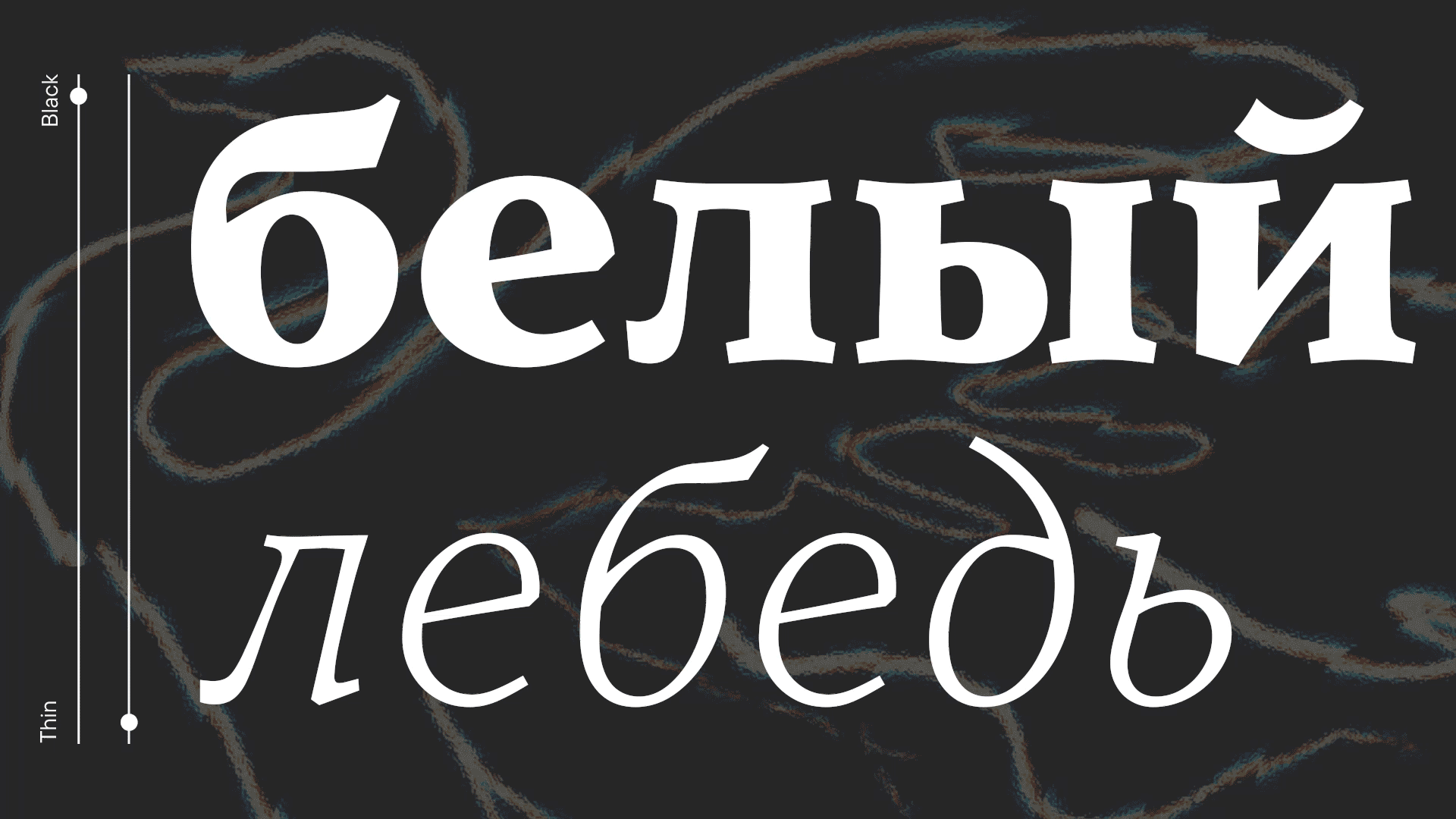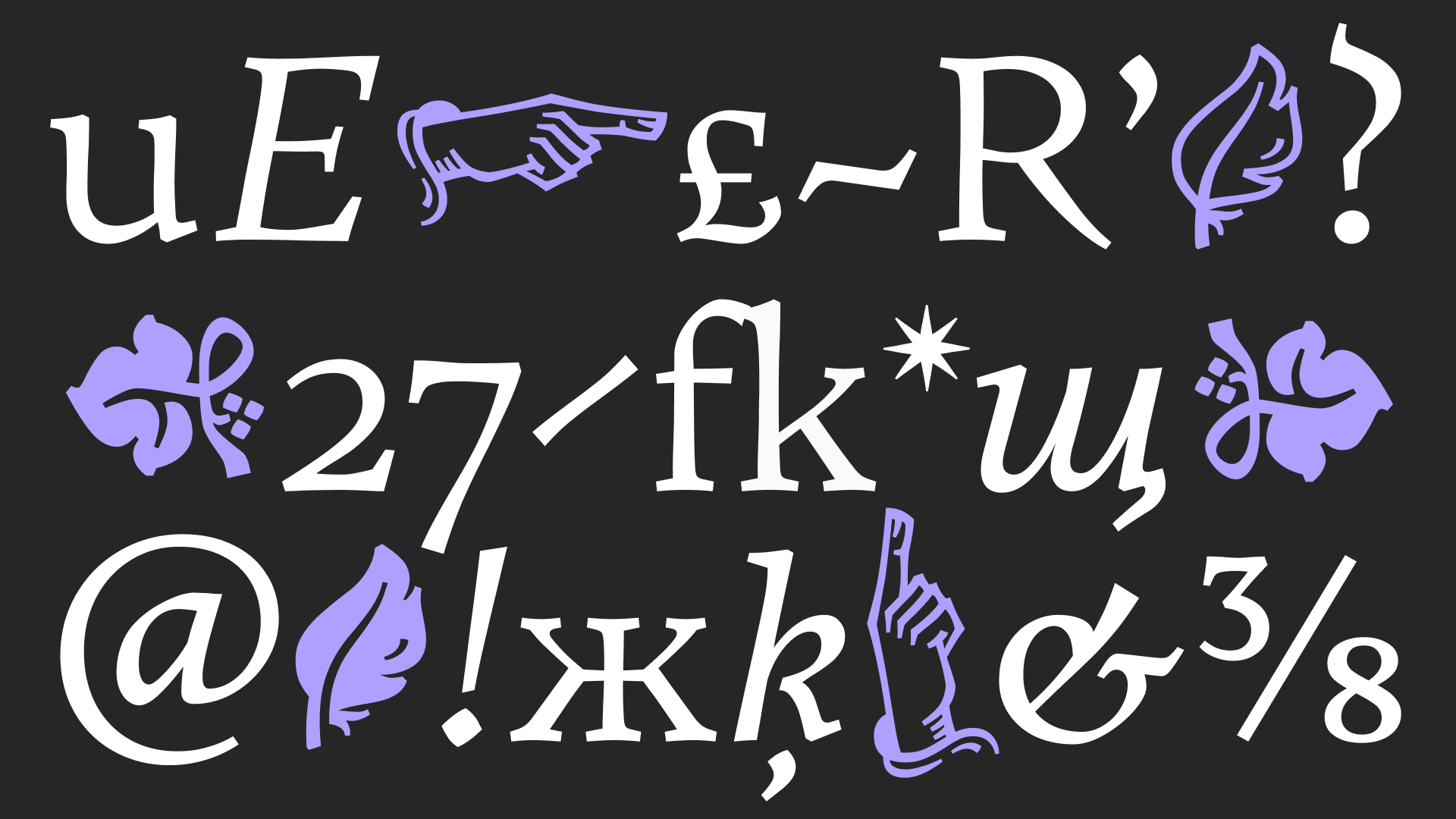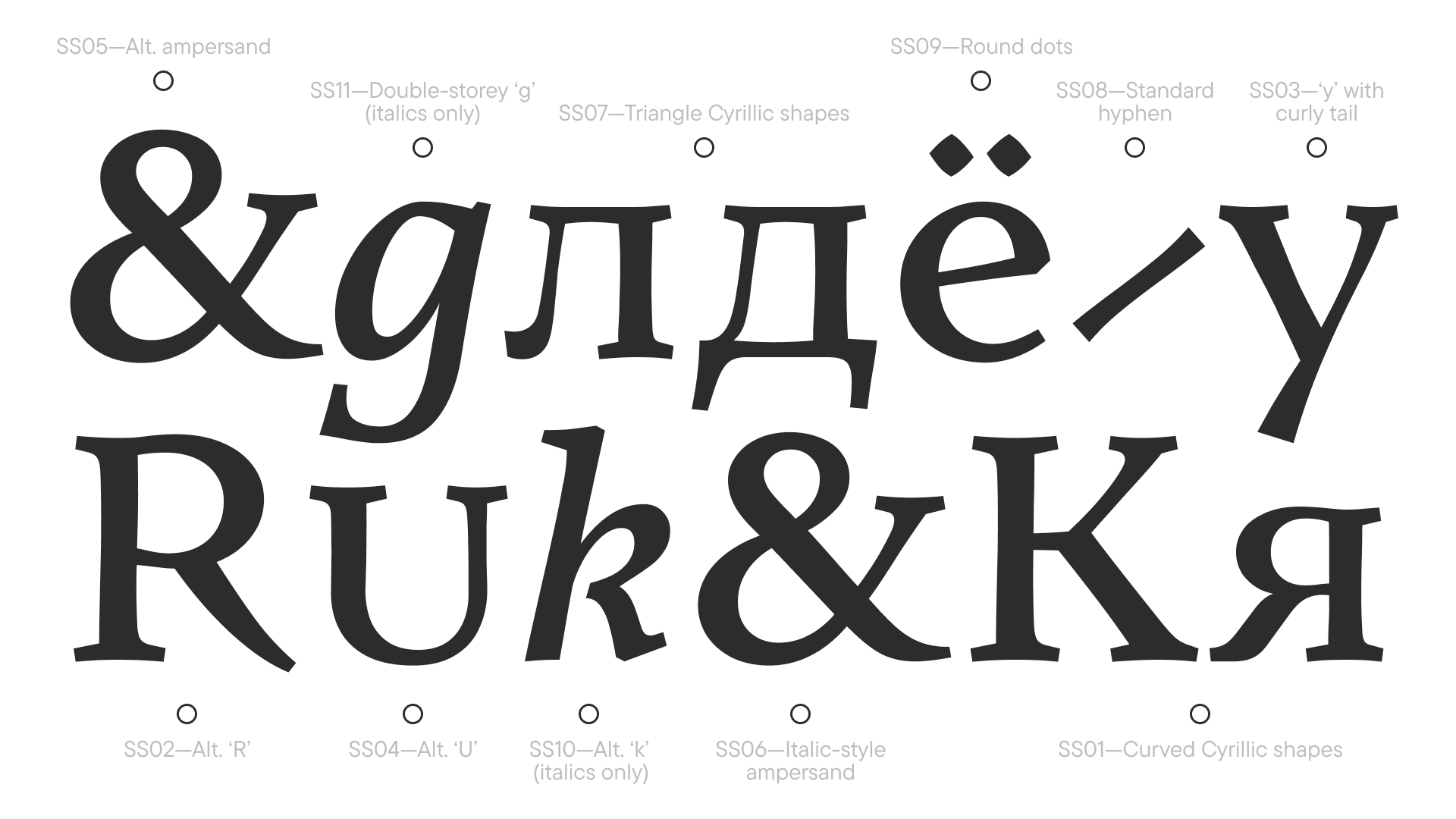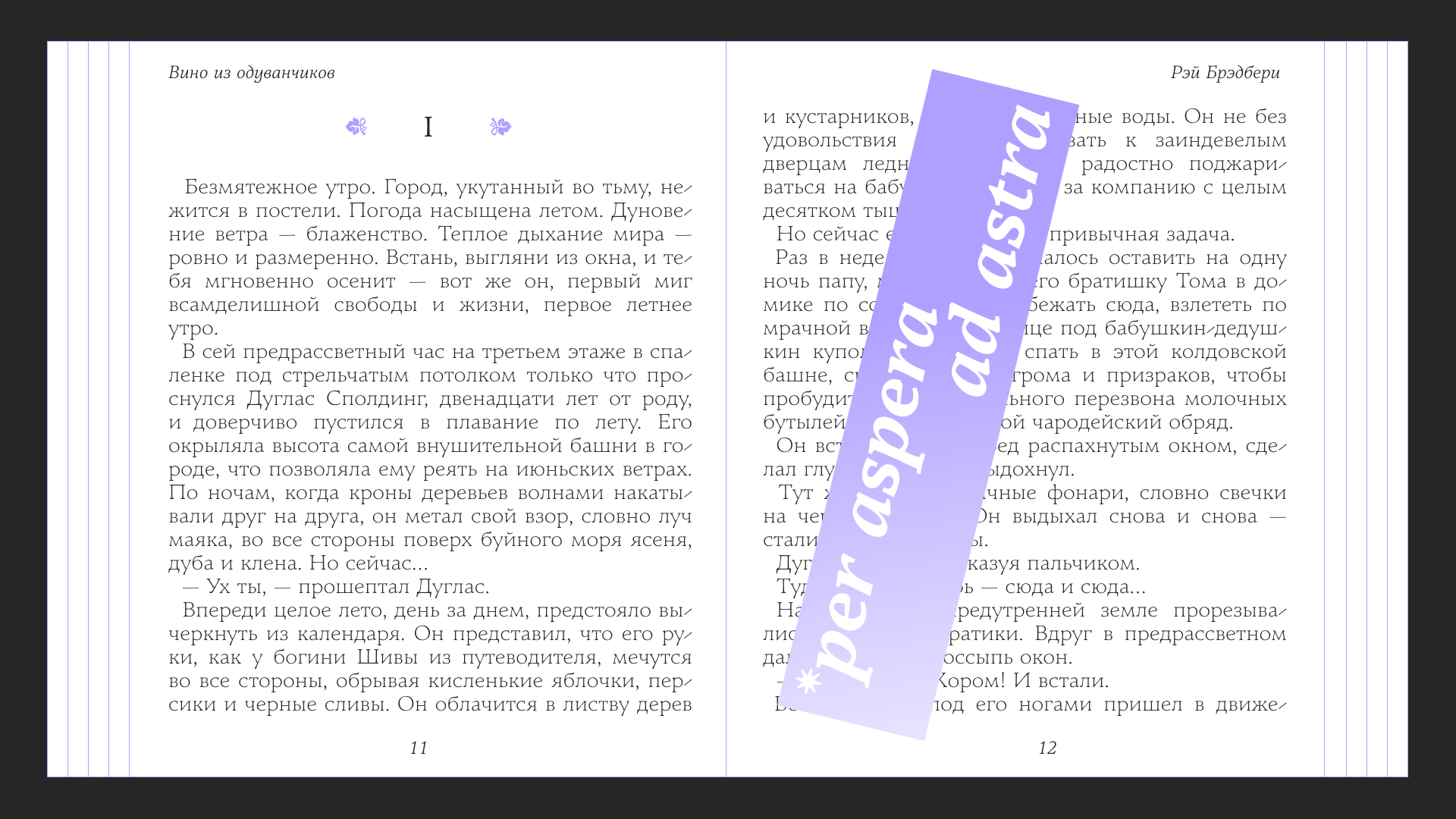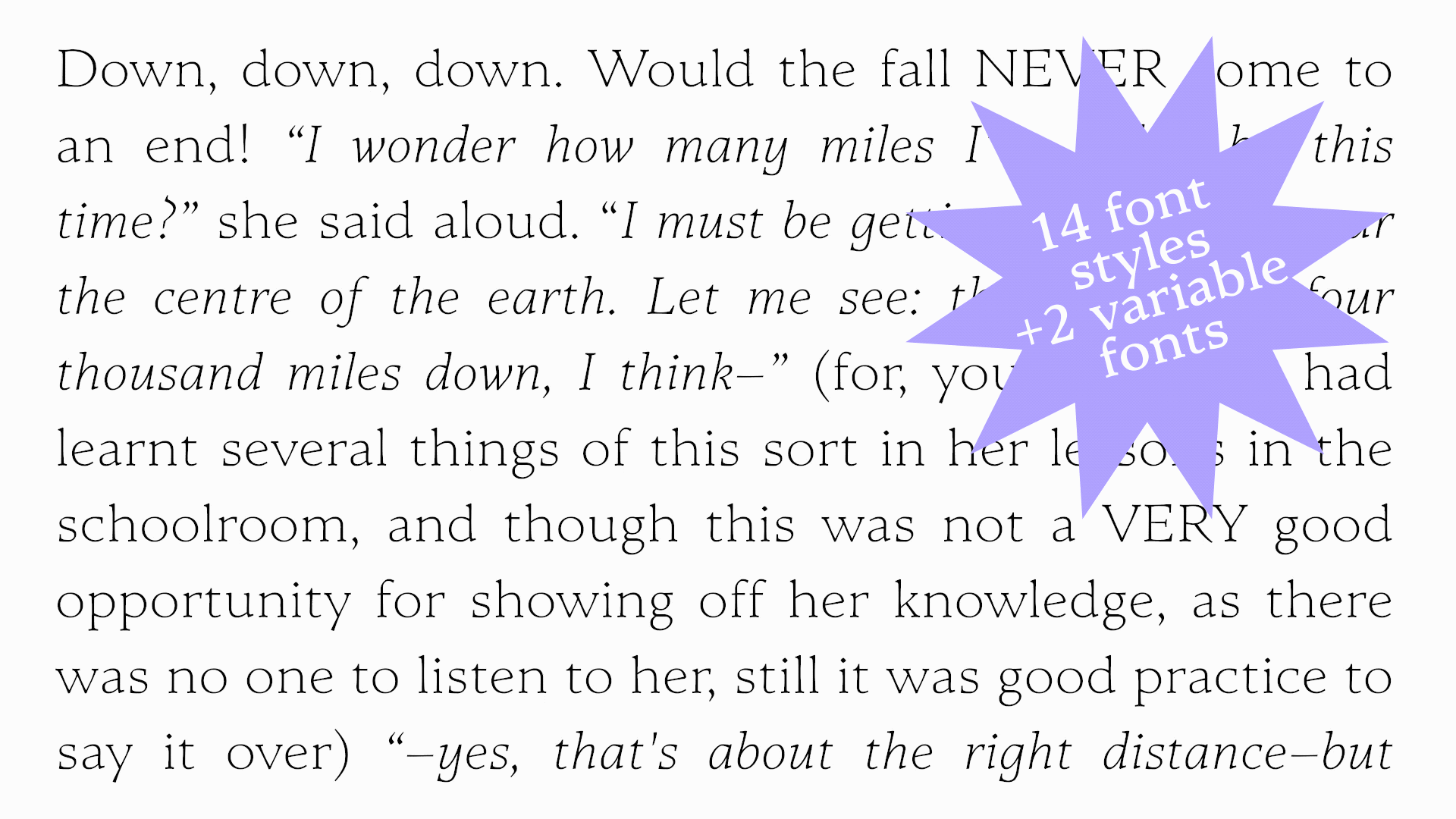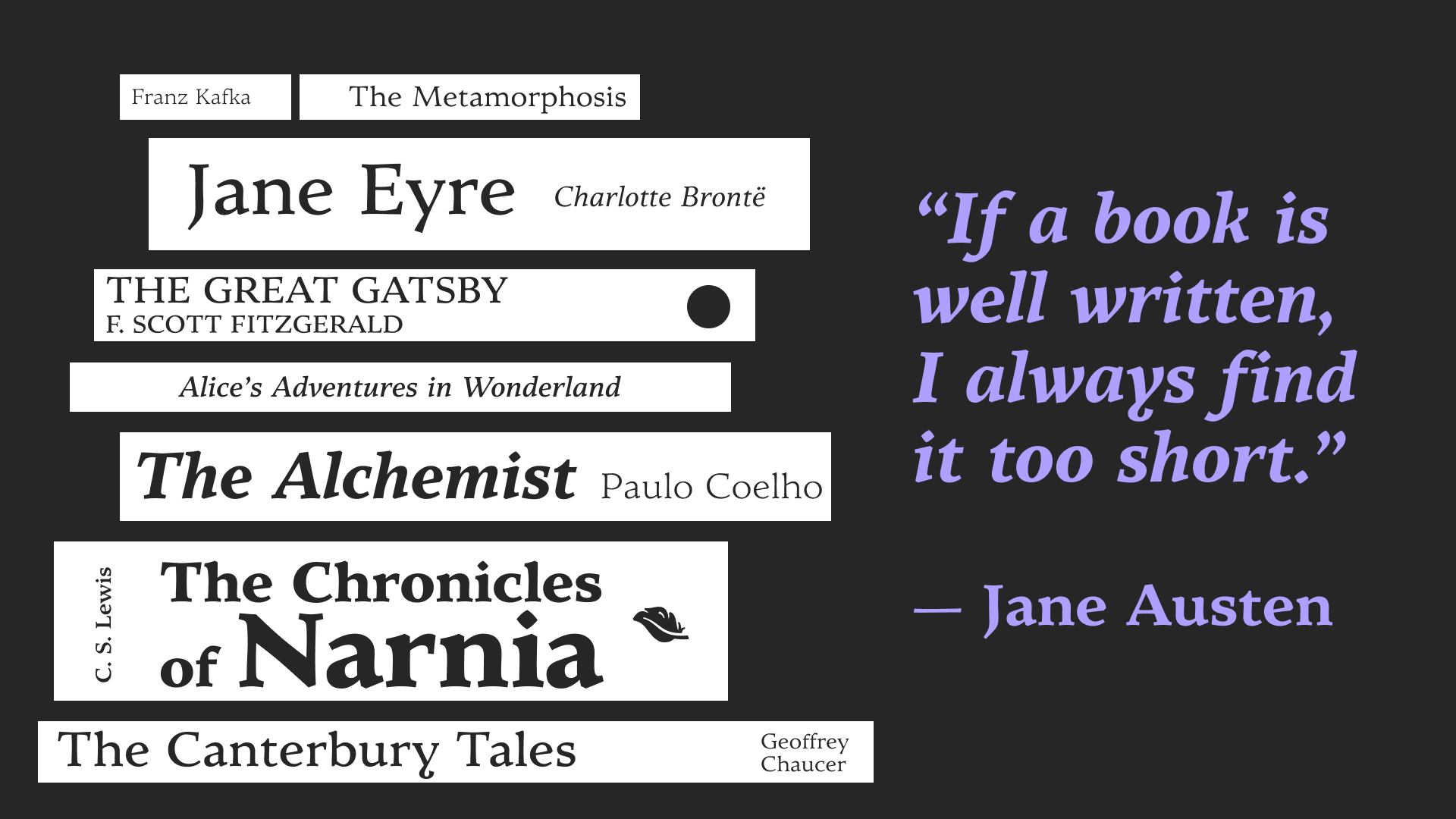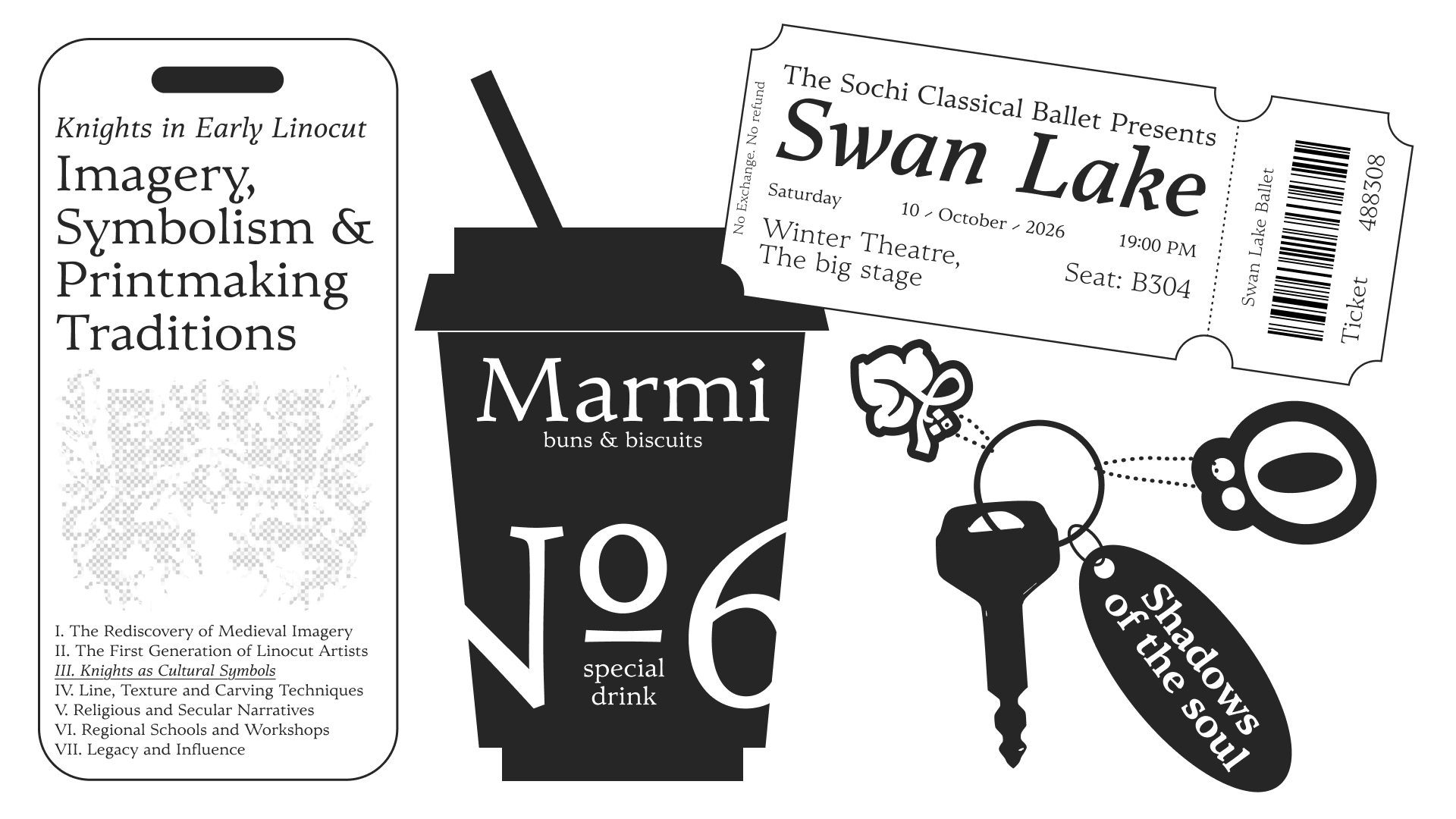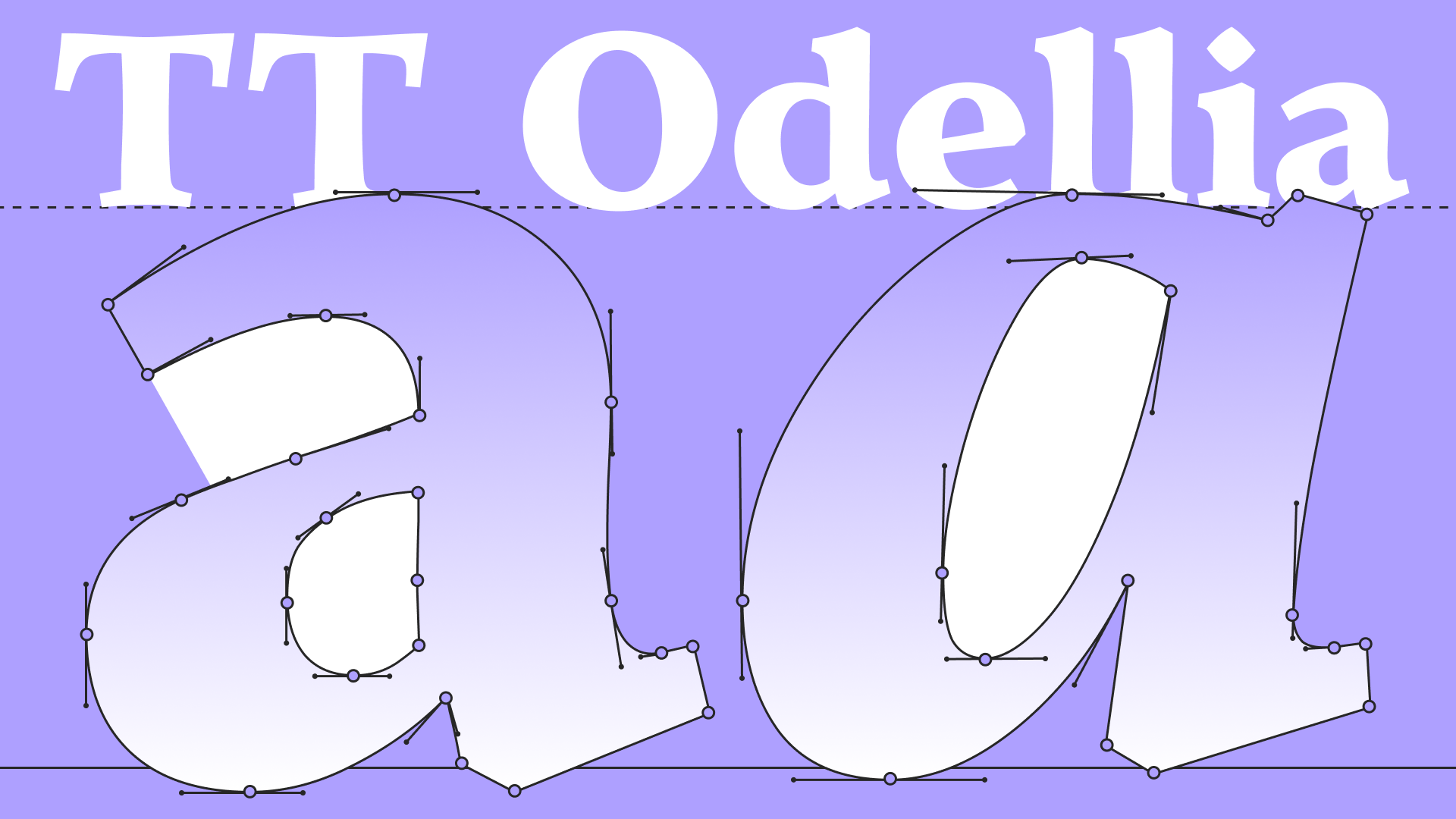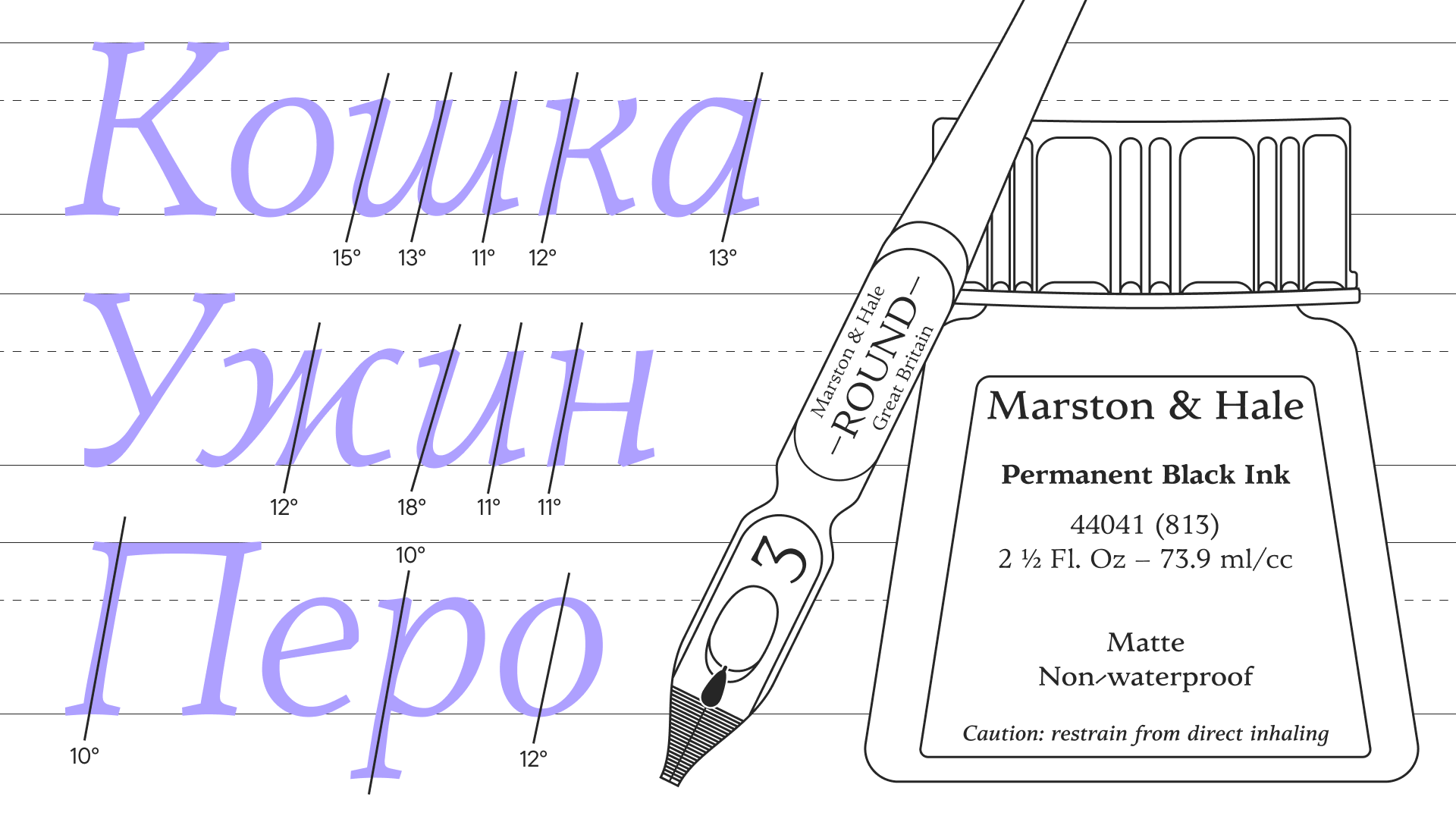
TT Odellia
TT Odellia — старостильная антиква с современным рисунком, вдохновлённая венецианскими шрифтами и классической музыкой. Она не повторяет классические образцы венецианских антикв: это их собирательный образ в современной интерпретации.
Концептуально шрифт представляет собой единство противоположных начал: динамика и подвижность стемов в сочетании с чётко очерченными формами и яркими засечками демонстрируют воплощение рукотворной идеи в цифровом формате. Это отражается в названии гарнитуры: в нём слились имена Одетты и Одиллии — героинь балета «Лебединое озеро», белого и чёрного лебедей. Их образы символизируют двойственность человеческой натуры через контраст добра и зла.
Классический вид TT Odellia дополняется ромбовидными точками и дефисами, выполненными под наклоном. Для более современного звучания их можно заменить на привычные формы. Альтернативные знаки позволяют сделать шрифт мягким и дружелюбным, более нейтральным или добавить историзма. Кириллица в шрифте отличается самобытным рисунком. Курсивные начертания с оригинальными формами хорошо работают как в паре с прямыми, так и в качестве полноценных текстовых шрифтов.
Шрифт изначально разрабатывался как текстовый и сохраняет читабельность даже в маленьких размерах. Однако благодаря выразительному рисунку он прекрасно работает и в заголовках. Его можно использовать для проектов, связанных с музыкой, историей и искусством, для набора текста в художественно-литературных изданиях, вёрстки меню и оформления этикеток.